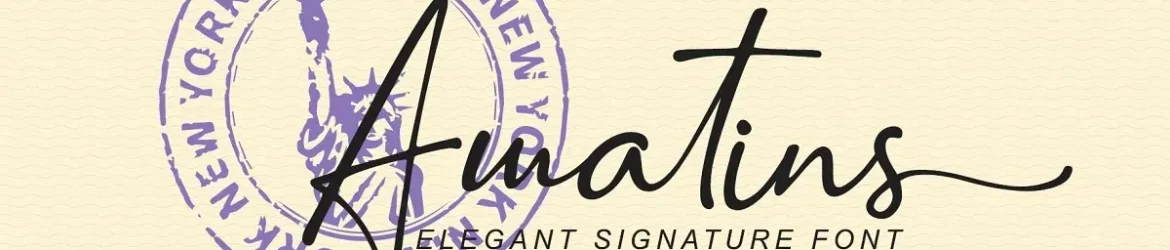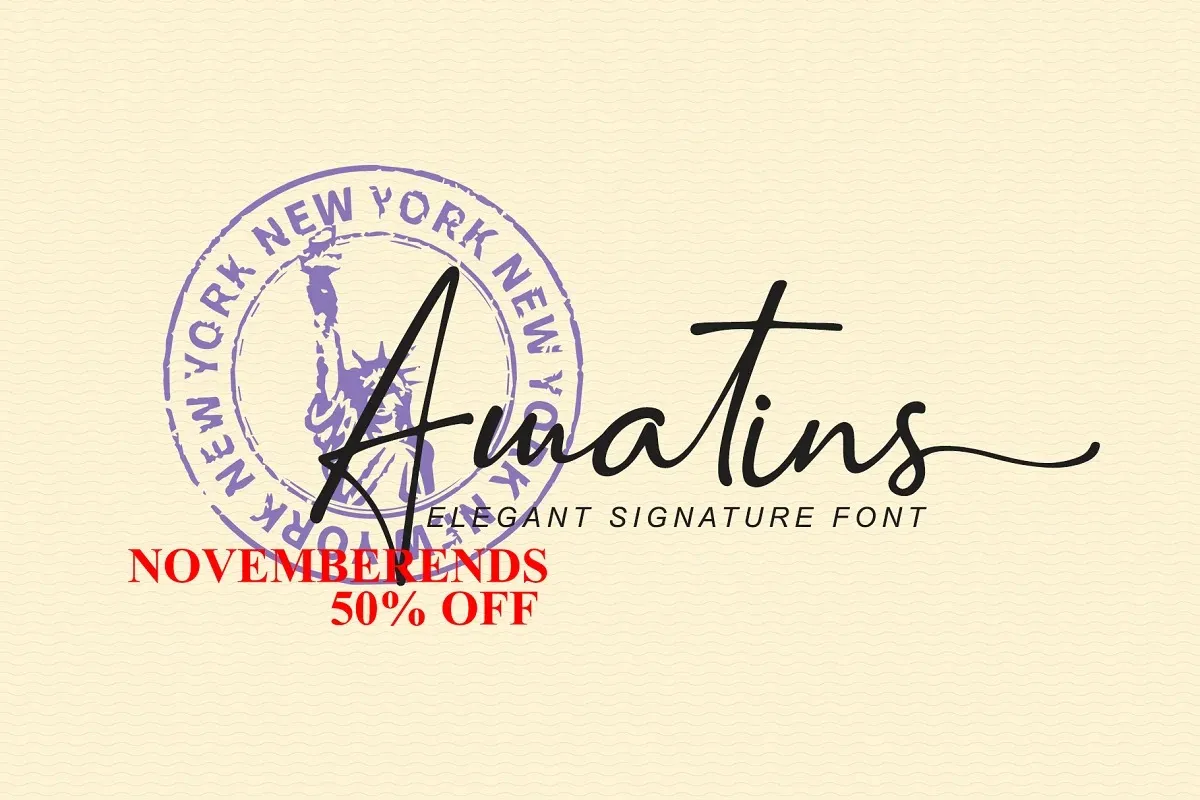
Amatins Font – Fonte Grátis
Amatins Font
A Amatins Font é uma elegante tipografia manuscrita criada pela BearyType, projetada para se destacar no design moderno tanto nos meios tradicionais quanto na web. Esta fonte é leve e fluida, perfeitamente adaptável a uma variedade de projetos, como fotografia, marca d’água, citações, cabeçalhos de blog, posters, casamentos, logotipos, moda, roupas, letras, convites e material de correspondência. Suas linhas fluidas garantem que você possa explorar inúmeras aplicações criativas ao usar esta fonte em diferentes contextos, tornando-a um investimento valioso para qualquer designer buscando uma solução de tipo atraente e versátil.